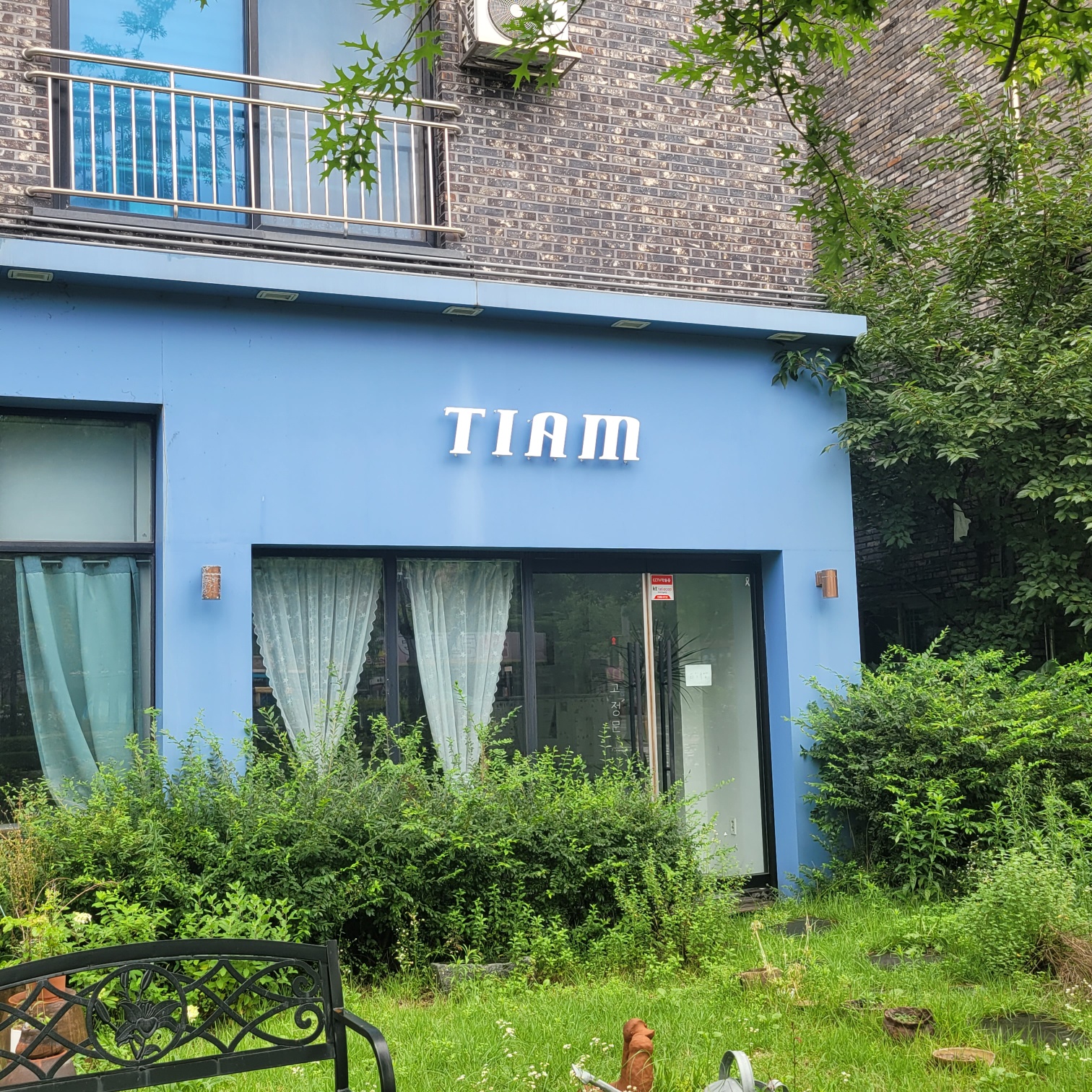
요게 무슨서체인지 알수있을까요? wlg*** 2023.08.09 이미지추적으로 해봐도 비슷한서체가 안나오더라구요 ㅠㅠ 서체가 정갈하면서도 개성적이어서 흥미가 생겨서 찾아보는데 너무 어렵네요,,, 댓글 0 등록 쉽고 빠르게 가장 비슷한 폰트를 알고 싶다면? 이미지로 검색하기
서체가 정갈하면서도 개성적이어서 흥미가 생겨서 찾아보는데
너무 어렵네요,,,